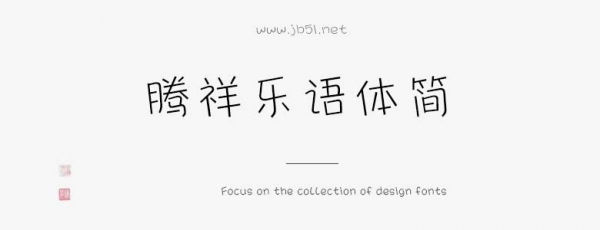
騰祥樂(lè)語(yǔ)體簡(jiǎn)是一款不錯(cuò)的藝術(shù)字體,由騰祥字庫(kù)出品,這款字體筆觸纖細(xì),書(shū)寫(xiě)流暢,適合應(yīng)用于藝術(shù)設(shè)計(jì)、平面宣傳設(shè)計(jì)、網(wǎng)頁(yè)設(shè)計(jì),書(shū)法字帖等領(lǐng)域,需要的朋友可以前來(lái)本站下載。
此款字為美術(shù)字。風(fēng)格鮮明、特點(diǎn)突出。筆畫(huà)悠然靈動(dòng)、字形斜勢(shì),如微風(fēng)徐徐,舒緩靈動(dòng),稚趣可愛(ài)。字形整體都保持同一個(gè)風(fēng)格??傊诓挥绊戦喿x的前提下盡顯其特征。本作品可適用于印刷出版兒童讀物、包裝設(shè)計(jì)、廣告設(shè)計(jì)、網(wǎng)頁(yè)設(shè)計(jì)等。